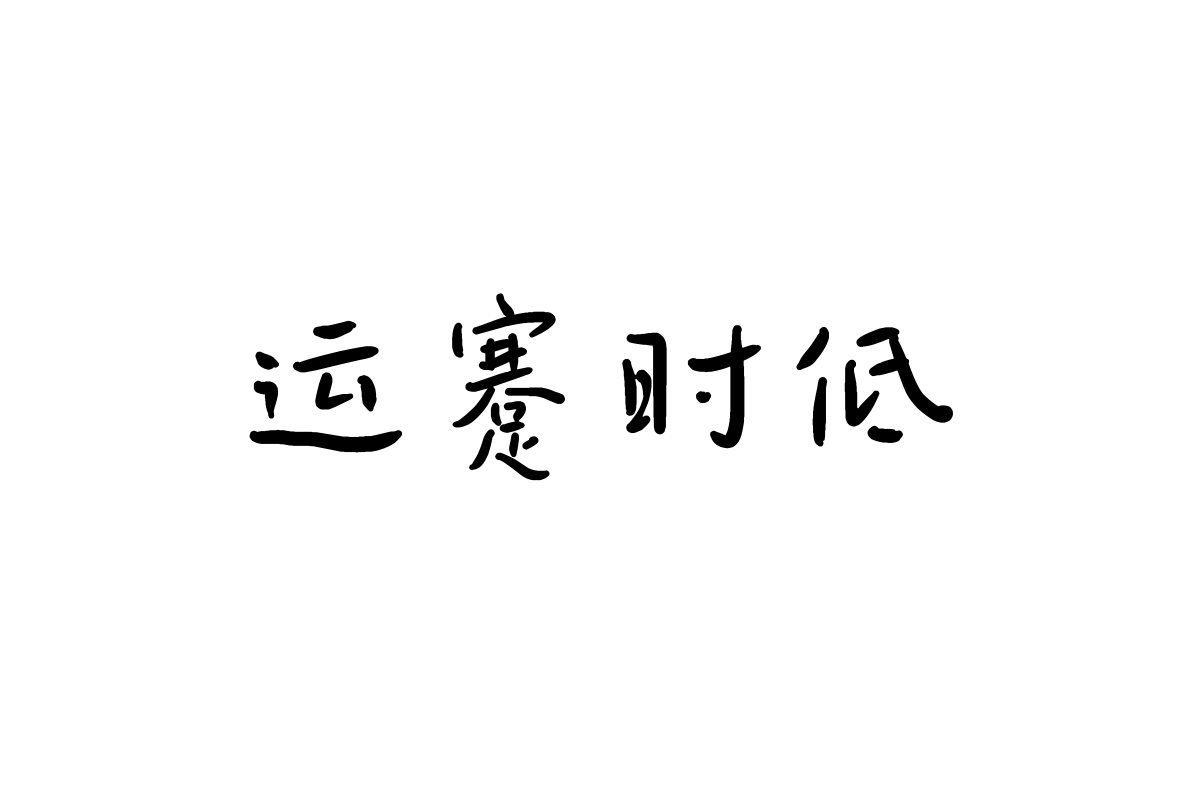
汉仪新蒂妙音体是一种中文字体,由汉仪公司设计。这款字体具有独特的艺术风格和现代感,适合用于各种设计项目,如广告、海报、网页等。它的字形流畅自然,线条柔和,给人一种优雅的感觉。此外,汉仪新蒂妙音体的笔画粗细适中,既不会过于粗犷,也不会过于纤细,这使得它在视觉上更加平衡。总的来说,汉仪新蒂妙音体是一款非常实用的字体,适合用于需要强调艺术感和美感的设计项目。